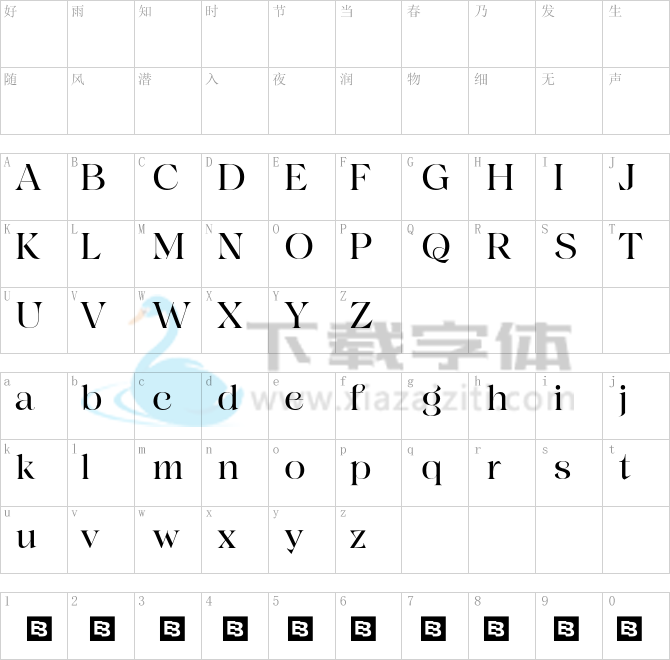
Amaline Trial.otf字体下载
Amaline Trial.otf字体下载,这款字体结构工整、笔画清晰,兼顾美观与易读性,适用于标题、正文、海报、包装、LOGO 等多种场景。字形优雅稳定,风格百搭耐看,适配日常排版与创意设计,让文字呈现更舒适、更具质感。Amaline Trial.otf字体下载一笔一画,皆是细节,以均衡的比例、流畅的线条打造舒适视觉体验,字形端正大气,风格简约现代。无论是商业设计、品牌宣传还是日常排版,都能轻松驾驭,让文字更有格调与力量。Amaline Trial.otf字体下载字体下载。